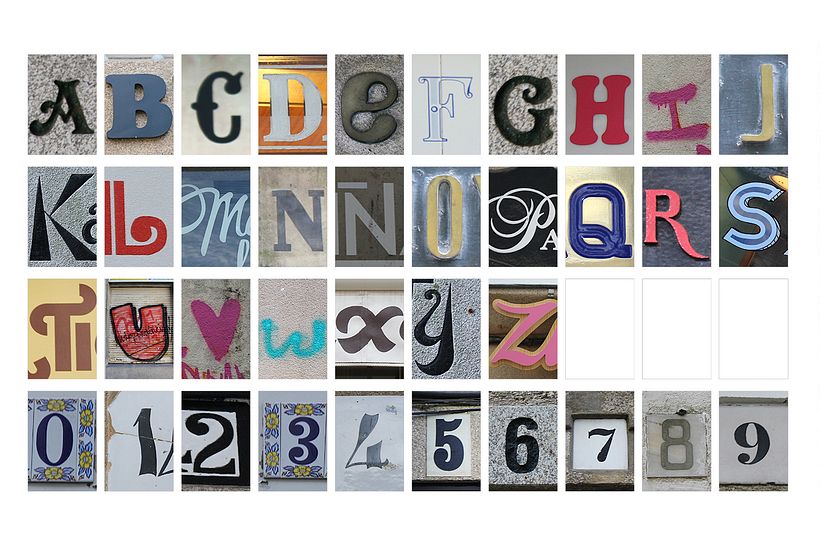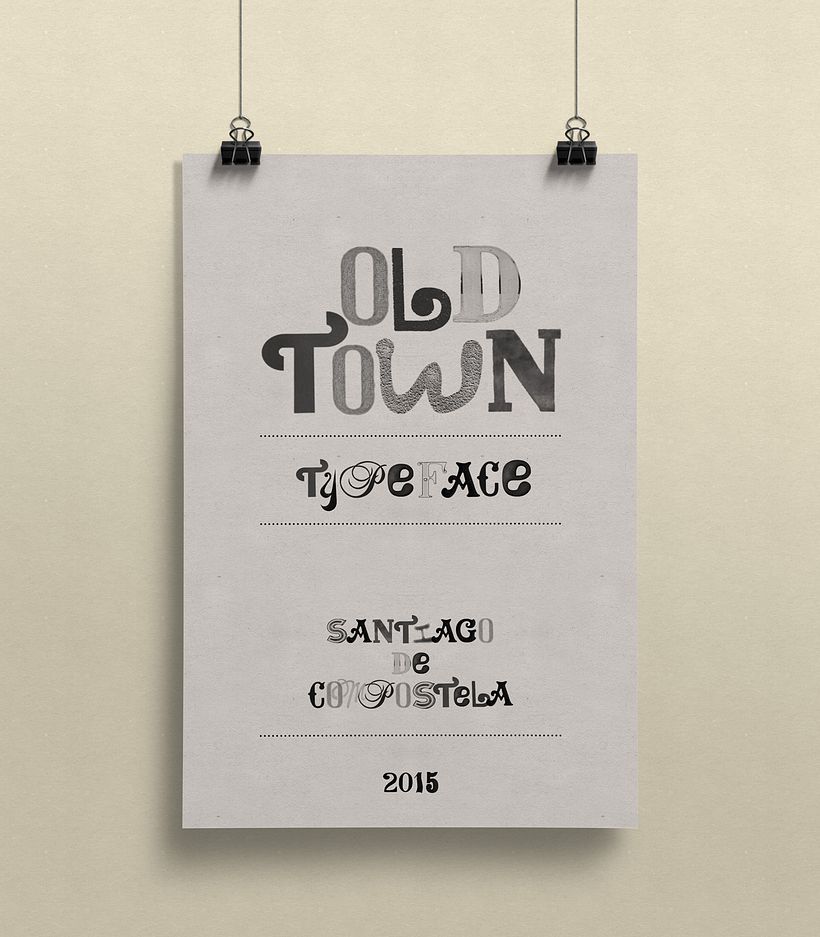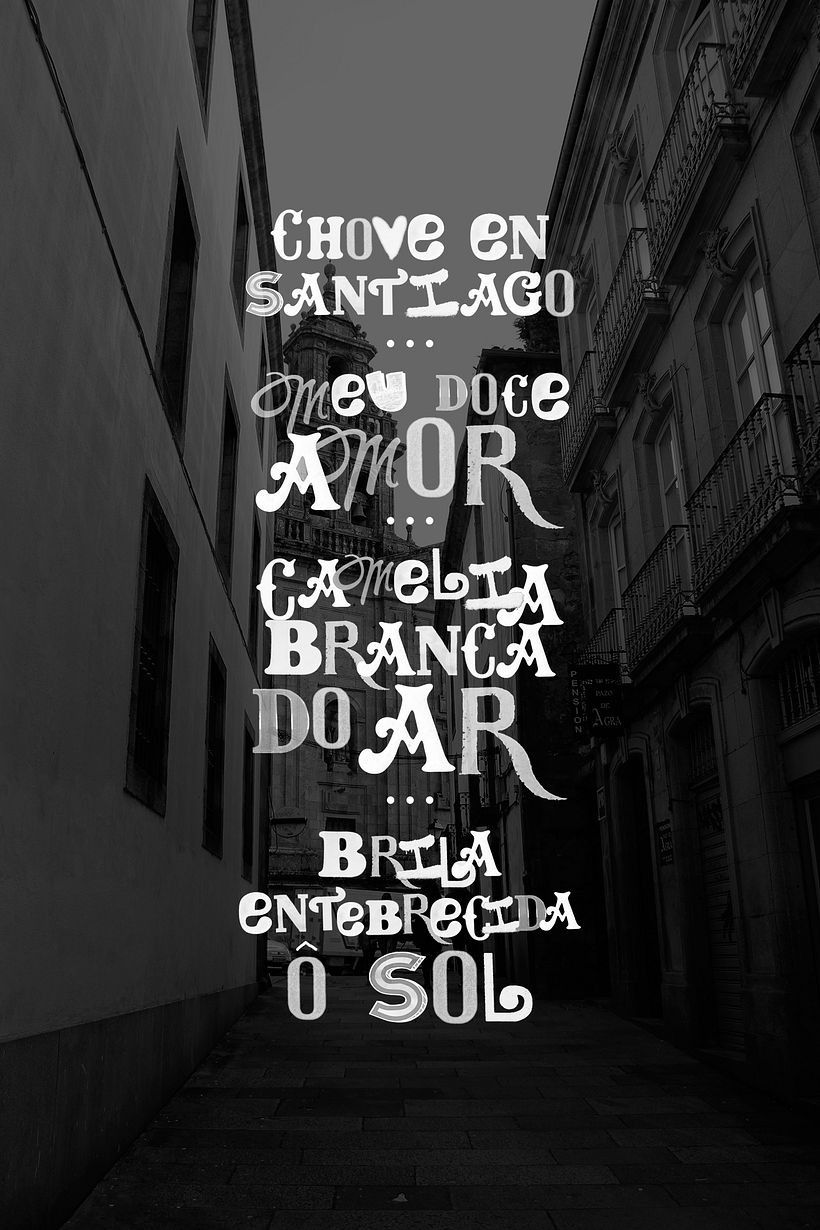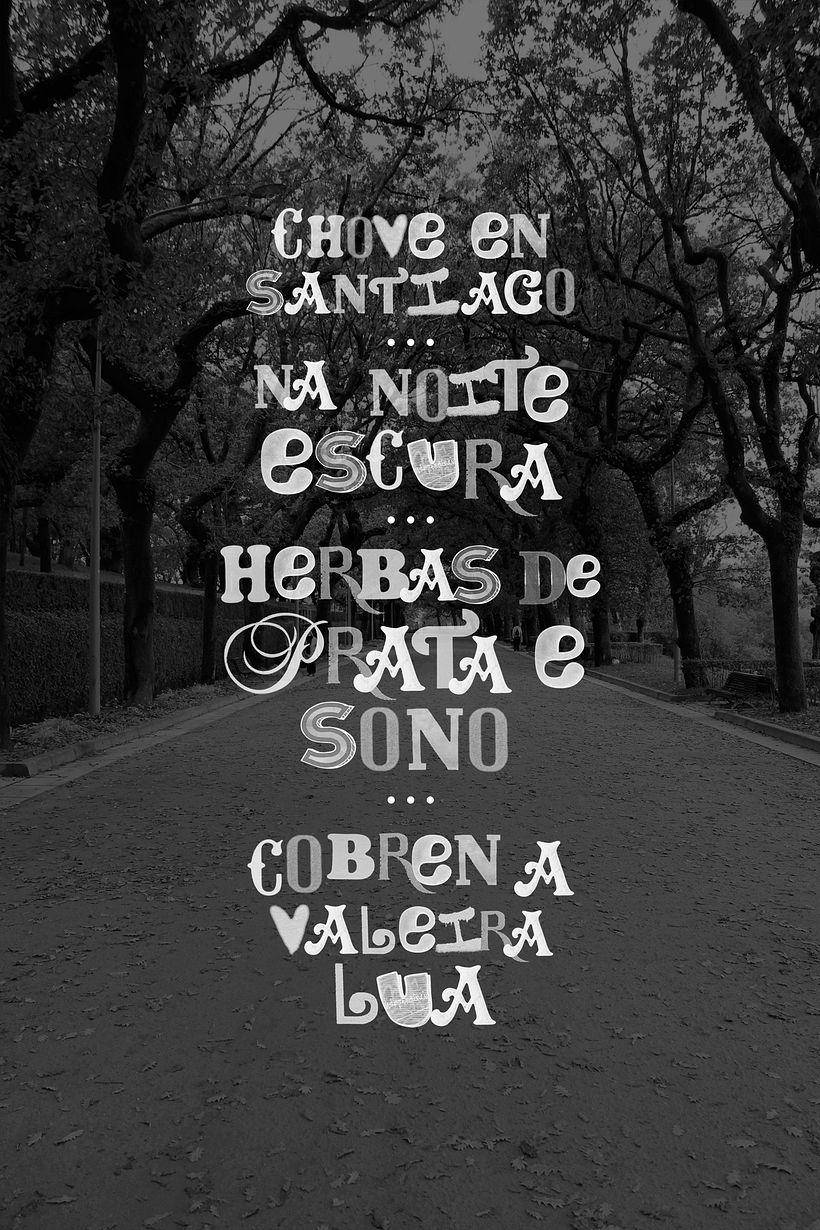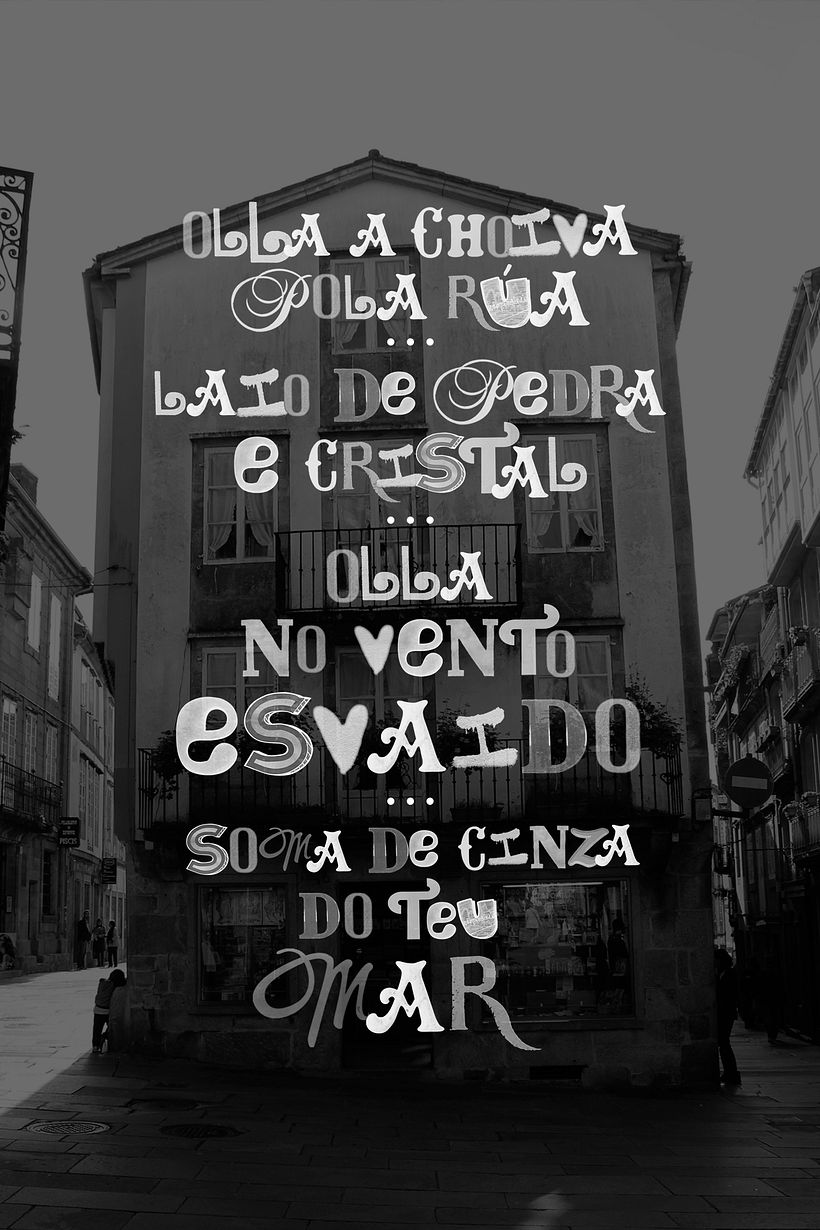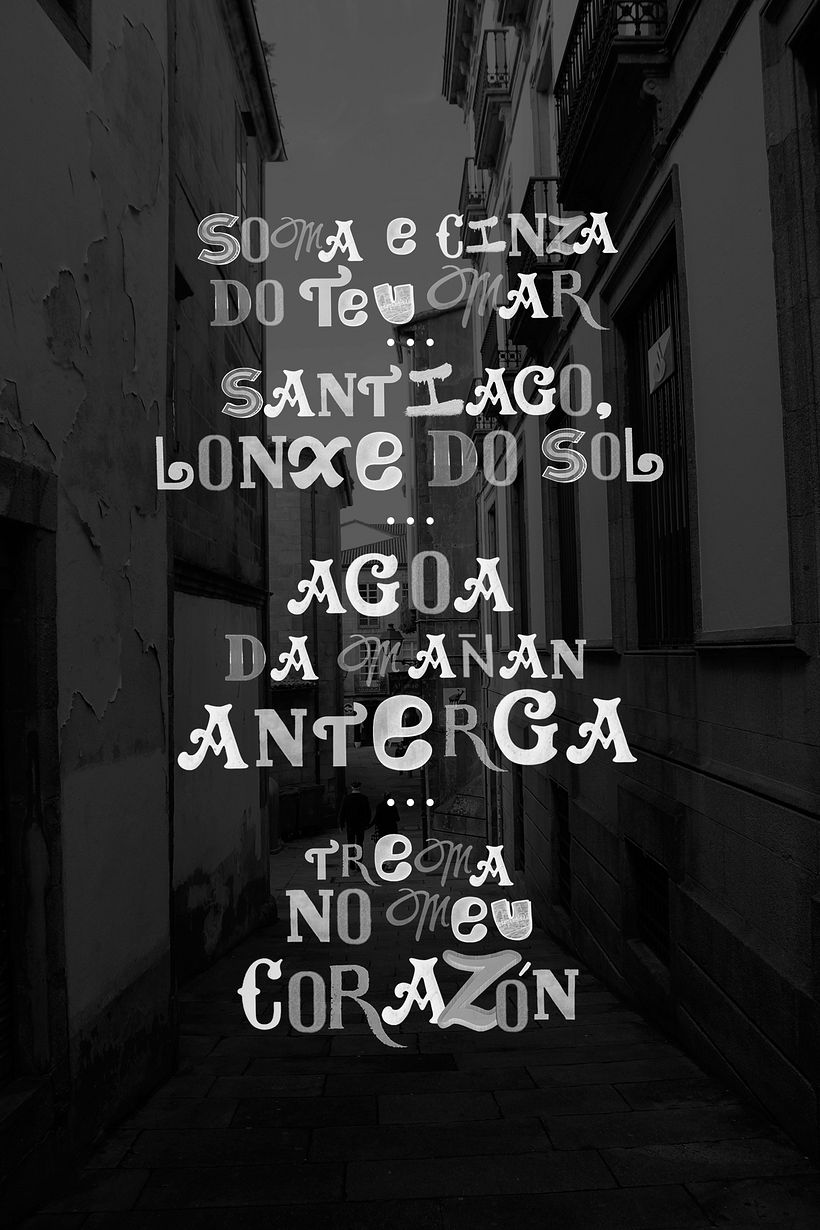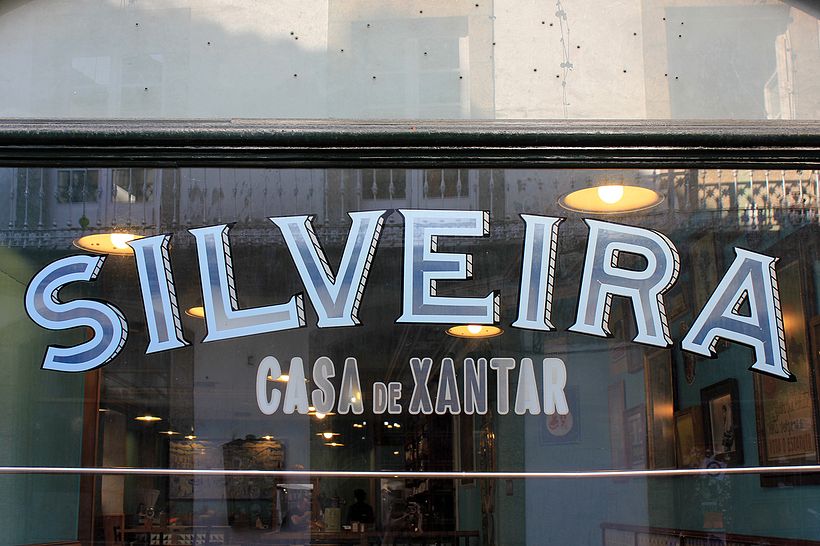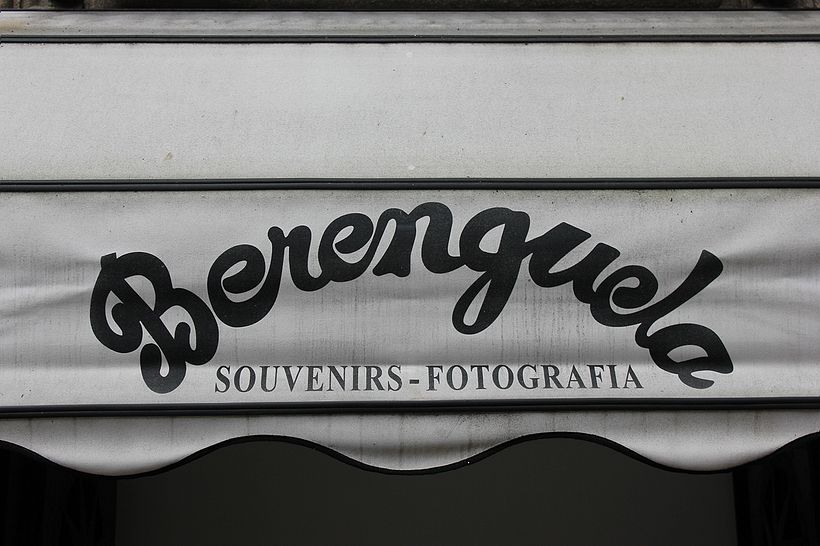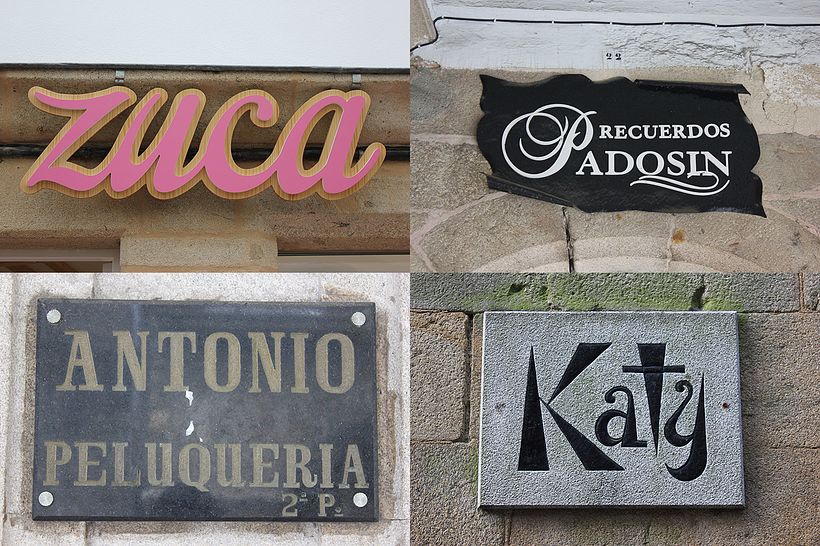
OldTown typeface
Result of a typographic safari through the historic center of Santiago de Compostela made in 2015.
The intention was to portray the diversity and variety (beautiful or not) of the city's typographic reality and search for a sense identity within it. Trying to cover all possible ranges (commercial signs, graffiti, city hall plaques, etc.) and without distinguishing between emblematic and temporary, this alphabet emerges, which is something like a typographic photograph of a specific moment in the Town.
Today, some of those signs no longer exist, others have been there for a century, and others won't last more than a year.
Welcome to OldTown:
Resultado de un safari tipográfico por el casco histórico de Santiago de Compostela hecho en 2015.
La intención era retratar la diversidad y variedad (bonita o no) de la realidad tipográfica de la ciudad y buscar en ella alguna identidad. Intentando abarcar toda las gamas posibles (rótulos comerciales, graffitis, placas del ayuntamiento...) y sin distinguir entre emblemáticos y temporales, surge este abecedario, que es algo así como una fotografía tipográfica de un momento concreto del Casco Vello.
A día de hoy, algunos de esos rótulos ya no existen, otros llevan ahí un siglo, y otros no durarán más de un año.
Welcome to OldTown: